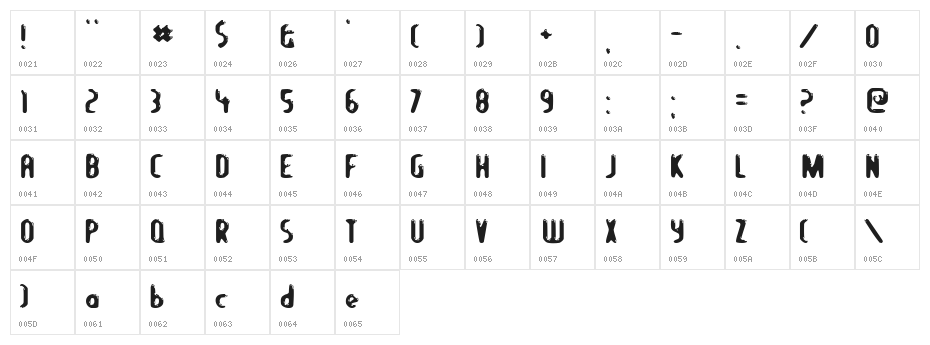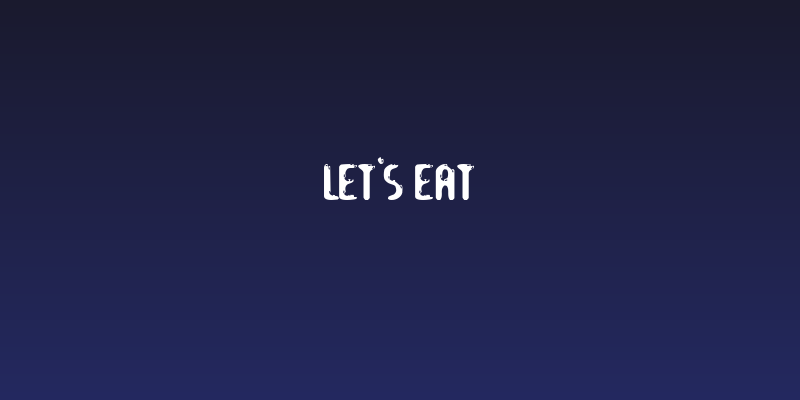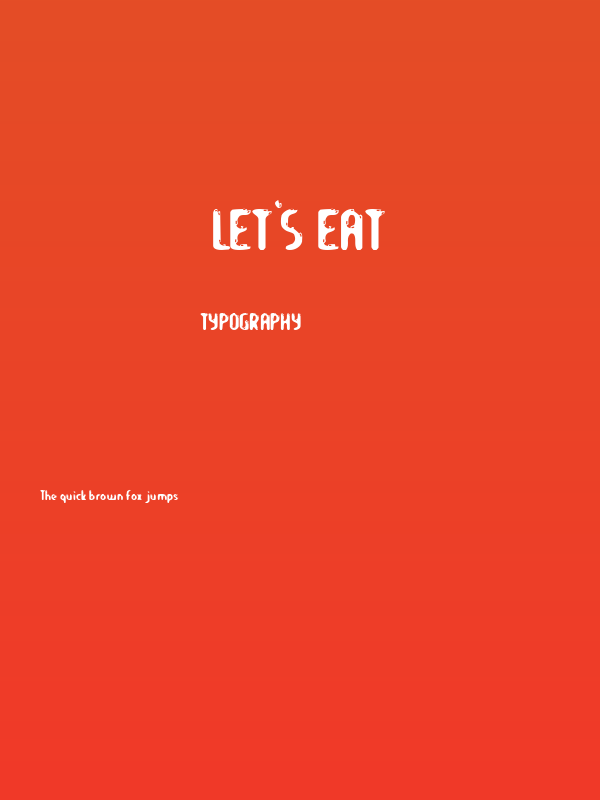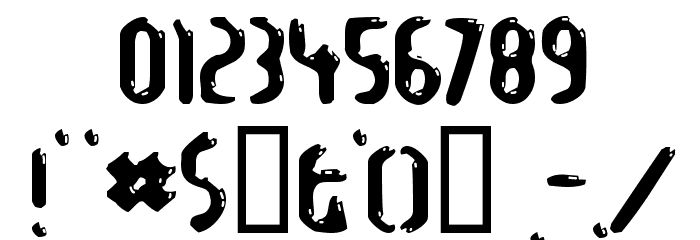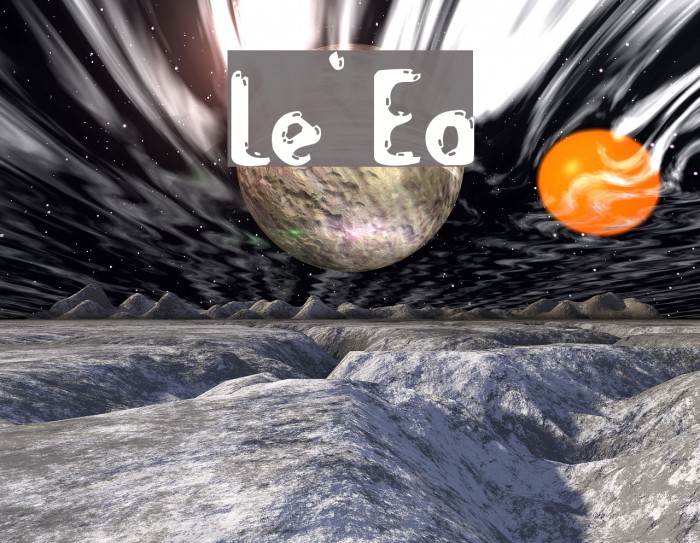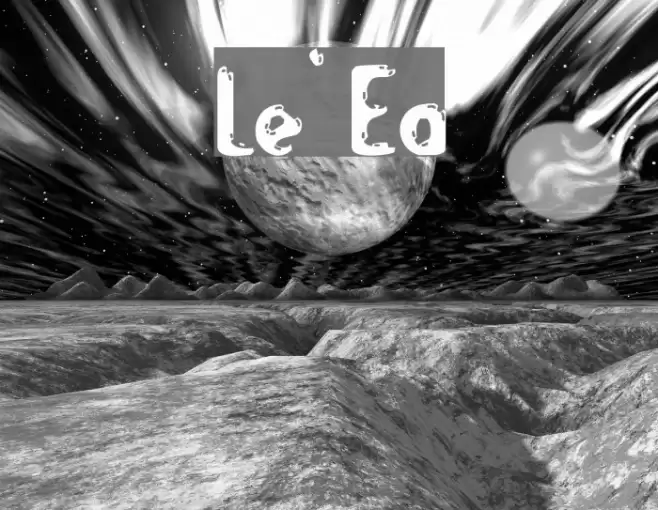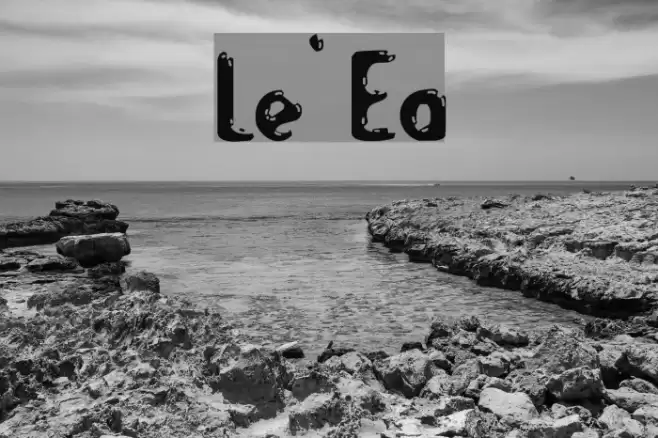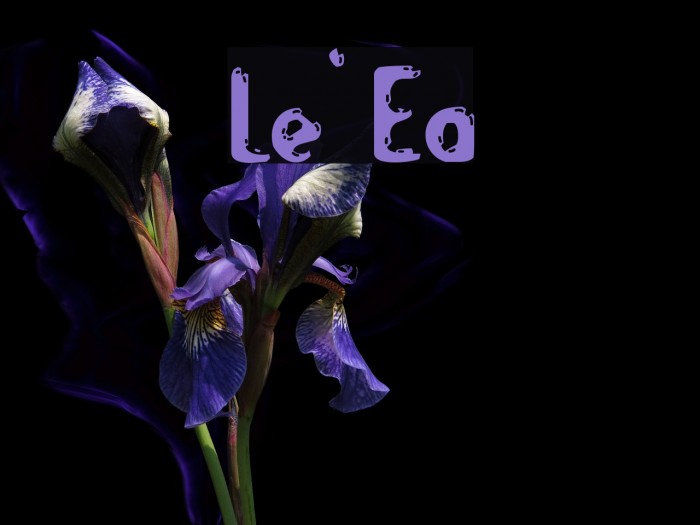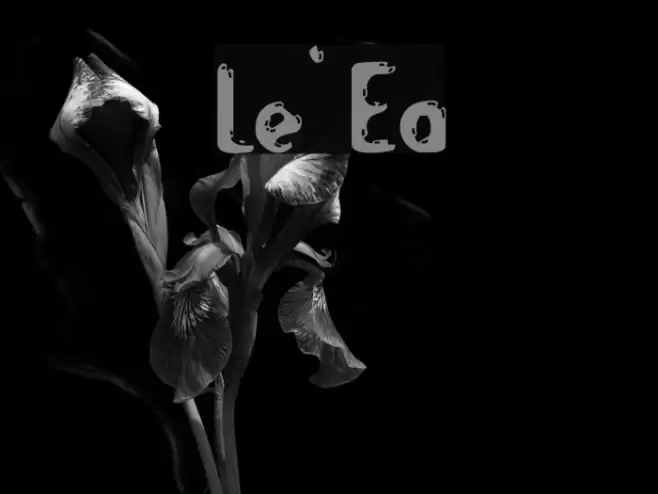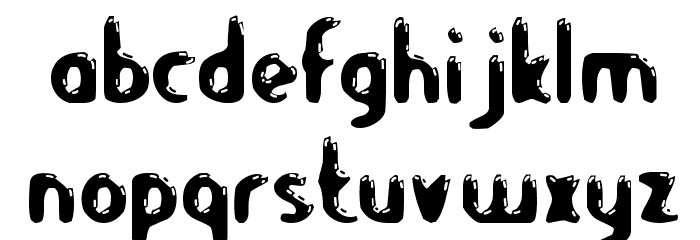
Let's Eat Font
| Style général | Vintage, Decorative |
| Projets proposés | Perfect for posters, album covers, branding for edgy or artistic businesses, and any design needing a bold, creative touch. |